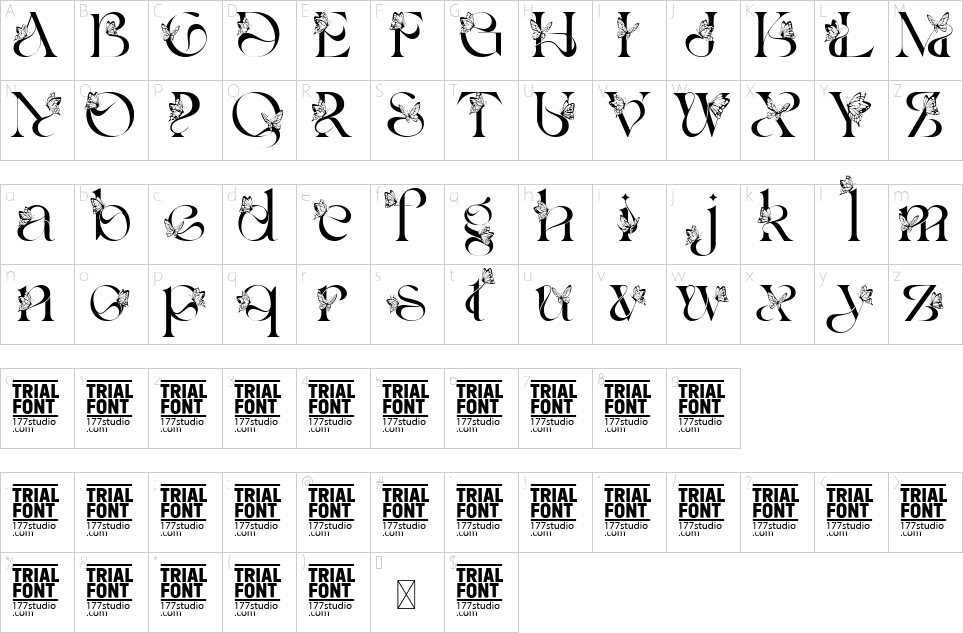
A fonte Marital é uma elegante e sofisticada escolha para aqueles que desejam um estilo elegante em seus documentos, e-mails ou anúncios. Desenvolvida pelo designer desconhecido, a Marital foi projetada para dar um toque único e graciosamente a qualquer texto. Essa fonte é perfeita para aqueles que buscam uma sensação de sofisticação, mas também mantêm uma personalidade discreta. Se você está procurando por uma fonte que permita um equilíbrio perfeito entre elegância e minimalismo, Marital é uma ótima opção. Com seu design minimalista e sua aparência sofisticada, a Marial adiciona um toque de elegância a qualquer projeto gráfico. Descubra por si mesmo o brilho da Marial ao fazer seu próprio projeto, pois é uma fonte gratuita que você pode facilmente usar em seu computador Windows ou Mac.